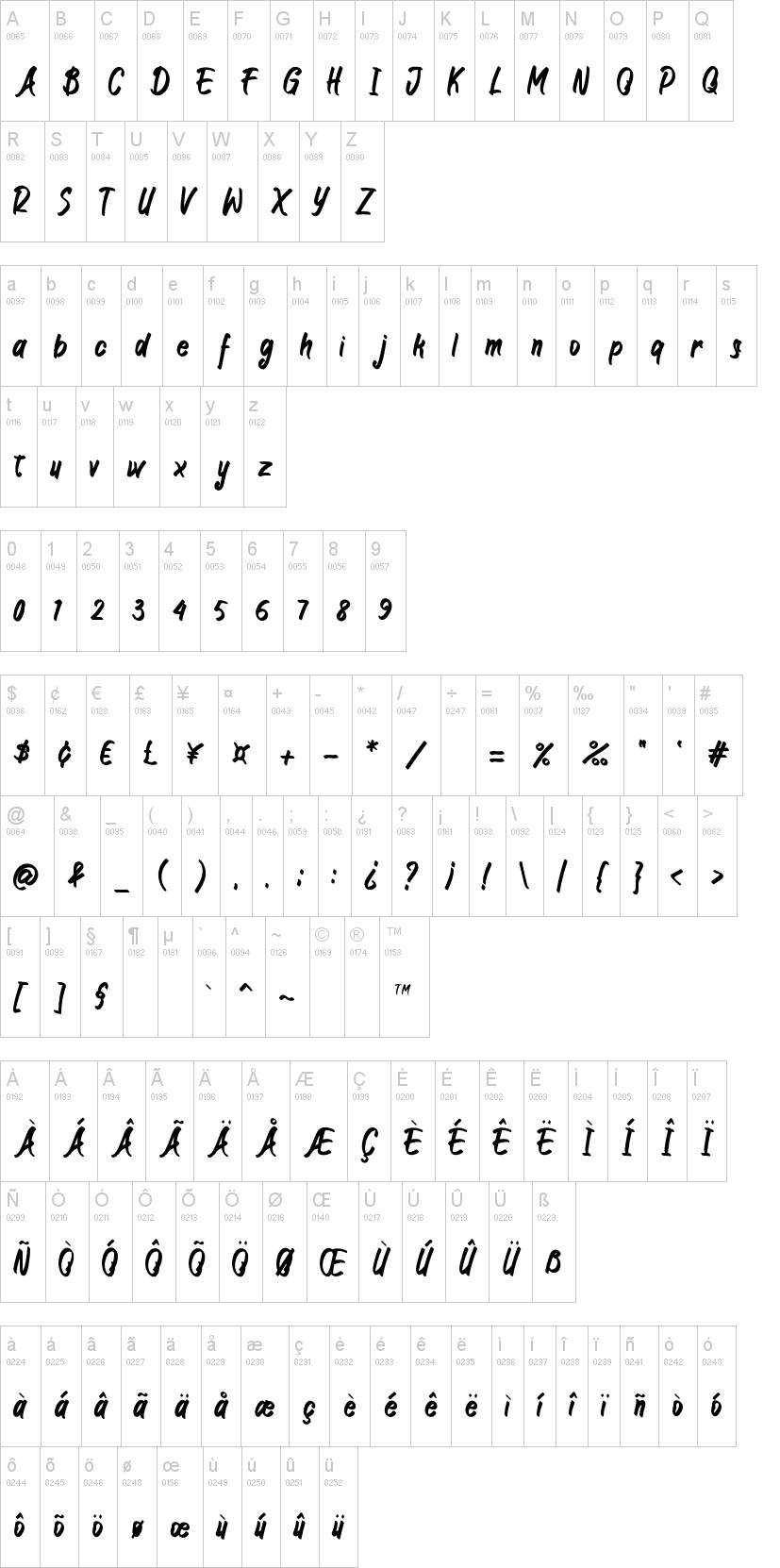
Jiangkrik
? Jiangkrik 字体是一种印尼式字体,由印尼设计师 Bambang Sulistyo 创作。该字体结合了传统印尼文化与现代设计元素,并采用了更加柔和的轮廓,使其具有更加柔和、现代、友好的外观。Jiangkrik 字体可以用于各种平面设计,例如标志、标题、海报、海报等,可以为设计师提供更多的创作空间。
Jiangkrik是一款非常不错的手写艺术字体,具有很好的视觉感,适合于文化类的宣传设计、商业类品牌的广告和产品包装设计以及个性化文字排版等较多场景。
Jiangkrik字符映射图